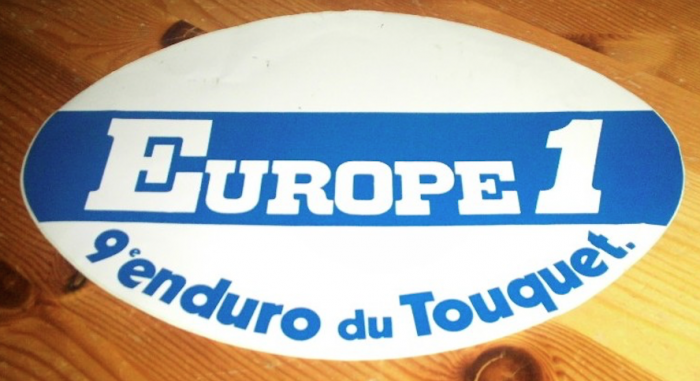
Schrift von EUROPE 1
Kennt jemand diese beiden Schriften. Die von EUROPE 1 sieht aus wie eine Courier, hat aber gerundete Ecken. Bei der anderen ist das schräge e markant.post-33573-0-68989500-1452430092_thumb.p